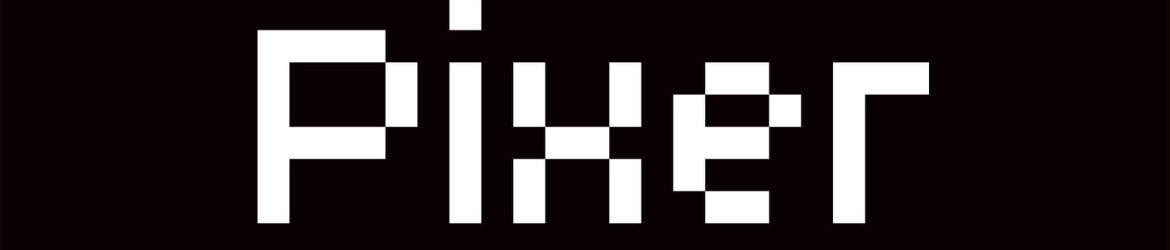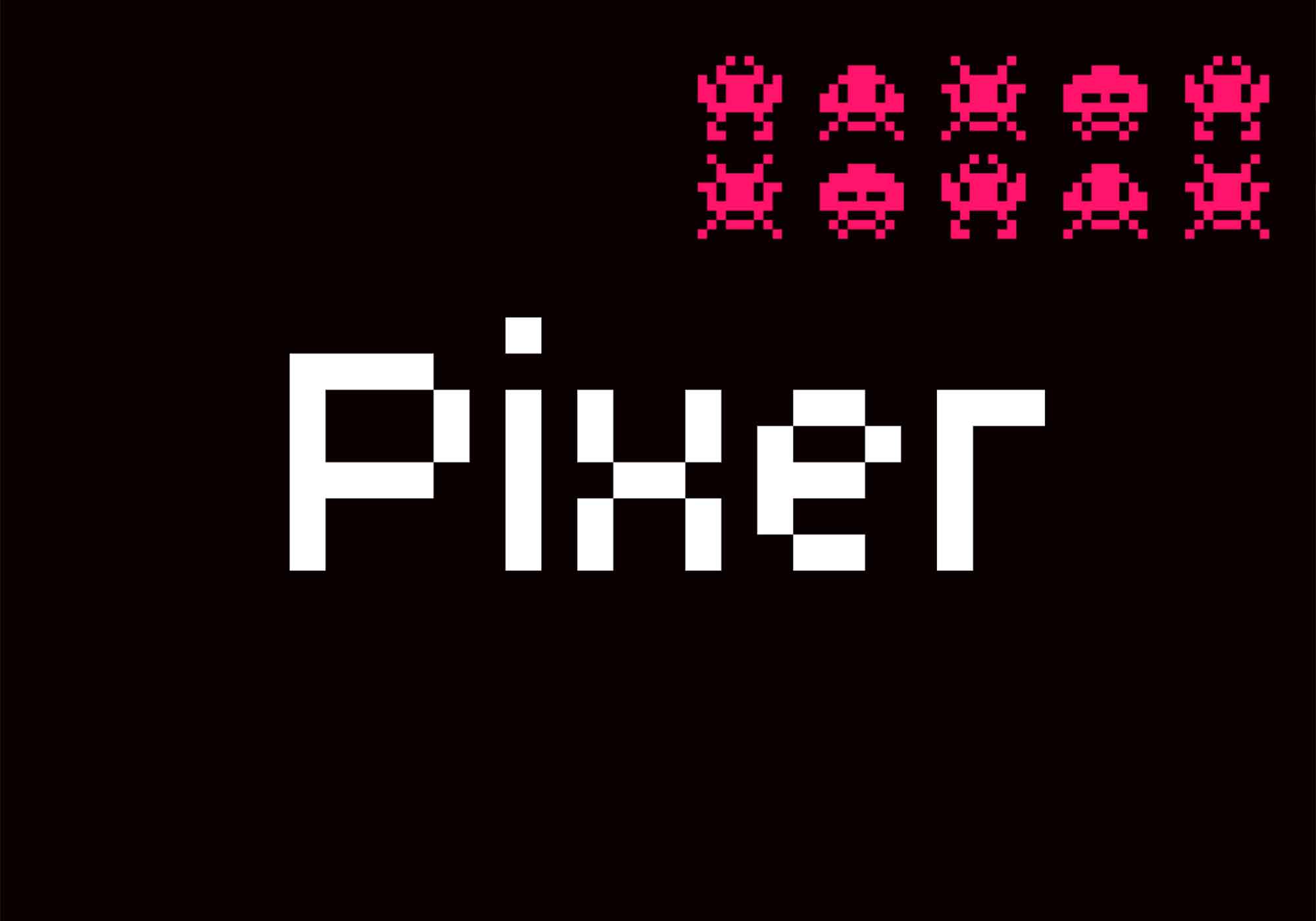
Pixer Pixel Font
Imagine a atmosfera nostálgica de uma loja de departamentos do início da década de 1980, onde a tecnologia eletrônica ainda era uma presença inegável, mas os produtos digitais eram menos comuns. Essa era uma época em que as lojas de móveis e artigos de decoração eram frequentadas por crianças e adolescentes, muitas vezes acompanhados de um adulto. Essa era uma época em que um arcade era mais do que apenas um lugar para jogos eletrônicos, era um ponto de encontro, um lugar para fazer conexões e se divertir. Arcades eram verdadeiros centros sociais, onde os moradores da comunidade se encontravam, faziam amigos e até mesmo formavam relacionamentos. Eles estavam lá para proporcionar uma experiência única e imersiva, com seus jogos em caixas de vidro polido, cada um com suas próprias histórias e características. É exatamente esse tipo de atmosfera que o Pixer Pixel Font pode capturar, com suas imagens pixeladas e claramente influenciadas pelos desenhos manuais dos anos 80 e 90.